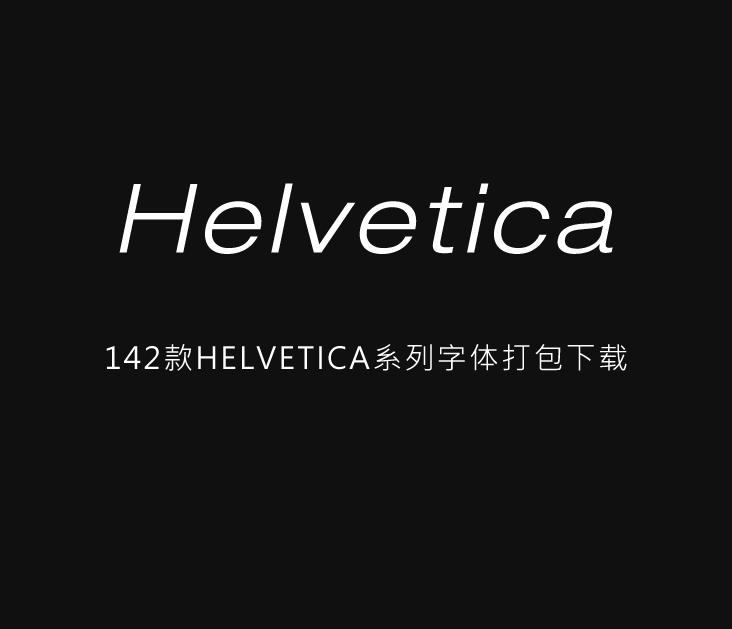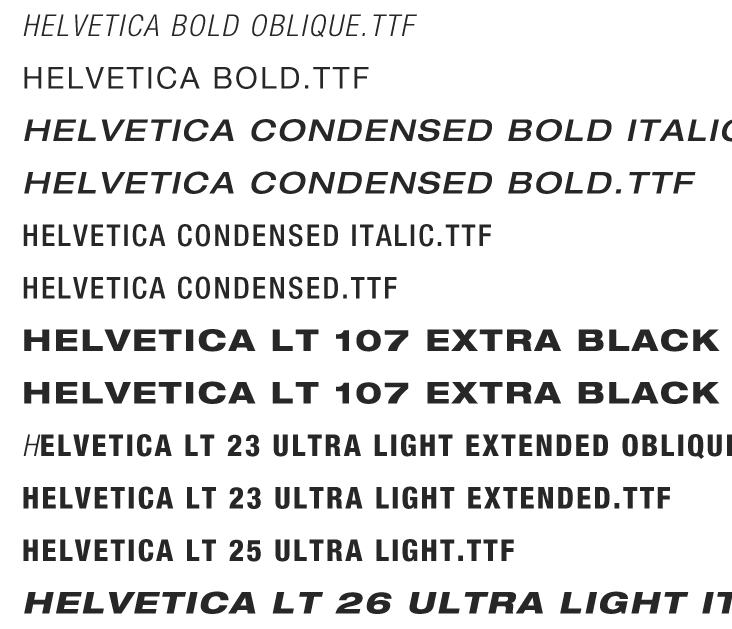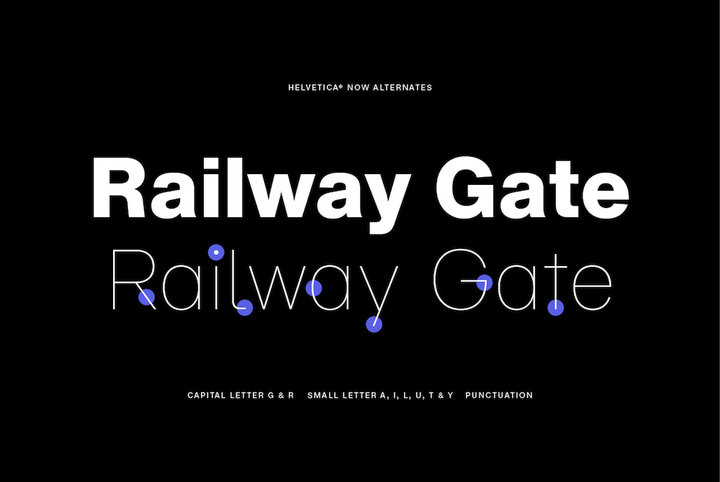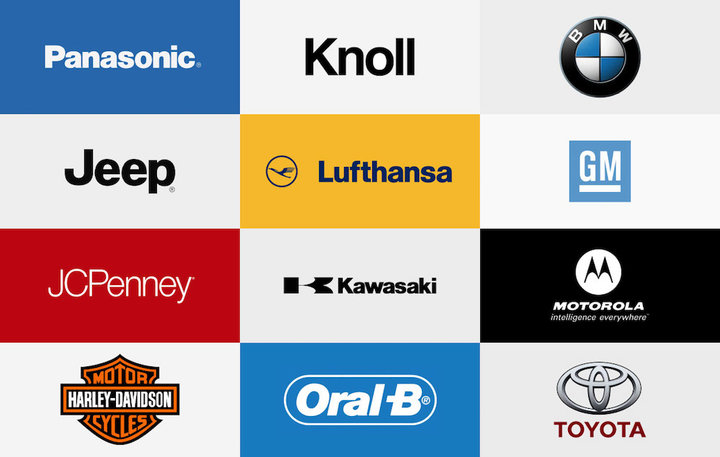
Helvetica是一种被广泛使用的的西文字体,于1957年由瑞士字体设计师爱德华德·霍夫曼(Eduard Hoffmann)和马克斯·米耶丁格(Max Miedinger)设计。
Helvetica是由米耶丁格和爱德华德·霍夫曼在瑞士哈斯铸造所作为排版铅字制作的。当时人们熟悉的是“国际字体风格”(也称为“瑞士风格”),比如Josef Muller-Brockmann在1896年推广的Akzidenz Grotesk这类无衬线字体,而哈斯希望能设计一套新的无衬线字体能够与Akzidenz Grotesk在瑞士市场上竞争。最初的名称是“Neue Haas Grotesk”,意为“哈斯的新无衬线铅字”,后来曾考虑改为Helvetia(源自拉丁文的“瑞士”一词),不过最终改为Helvetica,在拉丁文中意为“瑞士的”。
Helvetica被广泛用于全世界使用拉丁字母和西里尔字母的国家。同样的风格也被移植到希腊字母、希伯来字母和汉字。
Helvetica是苹果电脑的默认字体,与微软常用的Arial字体相似,但非自于它。2007年是helvetica诞生50年,作为在平面设计和商业上非常普及和成功的一款字体,英国导演Gary Hustwit专门为她拍摄了一部纪录片《Helvetica》。
Helvetica出自瑞士字体设计师Eduard Hoffmannh和Max Miedinger之手,体现了瑞士设计的理性主义精神,同时被认为是现代主义设计理念的典范。
《Helvetica》这部纪录片采访了老中青三代字体设计家,50、60年代进入设计界的老人深受现代主义影响,认为字体并不传达资讯,而要让人简单清晰的读懂文字;中年一代深受反主流文化的革命和后现代主义影响,认为设计应当是个人主义的,其极端就是难以辨认的垃圾风格的字体;青年一代设计师介于两者之间,他们更喜欢使用Helvetica,但不是没有选择的滥用。
在50年代,现代主义设计由于其风格简洁、朴素,并运用数量化的设计方法(典型的如画网格),Helvetica得以应用到商业设计中,成为大公司、政府等机构的御用字体,被70年代反主流文化的设计师们认为象征“权力”并且非常无聊。新一代的设计师,1970年代之后出生的人,虽然同样强调个性,但是他们同时不拒斥商业和机构,他们选择Helvetica放到合适的地方。
2019 年 4 月,Helvetica 字体更新了,距离这个传奇西文字体的上一次更新已经过去了 35 年。
之所以被称为传奇,是因为这个诞生于 1957 年的字体长盛不衰,从美国航空、松下电器、雀巢到纽约地铁标识系统,都有 Helvetica 的身影。它可能是应用最广泛的现代字体。
Helvetica 流行的原因是它就像一个透明的玻璃容器,能够清晰、可靠、中立地传达信息,同时让人意识不到字体的存在。有人把 Helvetica 称为「无衬线字体的终极形式」。
因此,它的更新周期也非常漫长。Helvetica 的上一次更新是在 1983 年推出的 Helvetica Neue(意为「新的 Helvetica」),新字体增加了更多的粗细和宽度,以适应桌面排版。
这一次,Helvetica 的改版历时 4 年,而且更加彻底,字体设计师重绘了每一个字体,并增加了 3 种视觉尺寸,目的很简单:适应更小的屏幕阅读。
从诞生到两次更新, Helvetica 字体的演进也代表了平面设计风格和传播介质的变迁。而最近的这次更新,Helvetica 似乎已经落后了。
这一次更新了什么?
Helvetica 这次更新后的名字叫 Helvetica Now。
拥有 Helvetica 字体版权的 Monotype 公司写了一篇短文介绍这个新字体,它的更新主要有三个方面。
1、三种视觉尺寸(Optical Size)
Helvetica Now 有三种适用不同场景的视觉尺寸:Micro、Text 和 Display。其中 Display 主要用于标题文本,Text 用于正文,Micro 是这次新推出的尺寸,用于在平板电脑、智能手表等小尺寸高分辨率屏幕上。
参与此次字体重制的设计师在接受 TheVerge 采访时解释了这样做的原因,对于他来说,Helvetica 通常在 6pt(点,字体度量单位,1pt = 1/72 inch = 0.3528 mm)时就变得难以辨认。
Micro 尺寸调整了字形和字距,可以让它即使在 3pt 下,也能够被轻松辨认。
2、可替换字形
为了给设计师更多的选择,Helvetica Now 为一些字母提供了可替换的字形,过去,设计师只能手动进行修改。比如,大写「R」最后一笔可以变直,小写的「a」可以用单层的结构,小写「i」的点可以用圆形。
3、字体细节调整
「Helvetica Now 不是一次更新,而更像是一次重制。」
这次字体的改版历时 4 年,Monotype 的设计师重绘了每一个字符,Helvetica Now 包含 9 个字重(从极细到超黑),3 种视觉尺寸和 2 种斜体,而每一个样式下包含字母、数字、符号等共有 815 个字符,所以,字体设计师义工重绘了四万多个字符。
微博用户 @字体主义 把 Helvetica Now 和旧版的 Helvetica Neue 做了一个对比,认为「字符整体更现代了,更偏几何风格。」
▲蓝色为 Helvetica Now,红色为 Helvetica Neue. 图片来自:@字体主义
Helvetica 为什么成为传奇
Helvetica 的诞生是二战后全球化思潮和设计上的现代主义交织的结果。
独立制片人导演 Gary Hustwit 的纪录片《Helvetica》详细解答了这个字体诞生的背景。战后,人们开始致力于减少国家间的贸易壁垒,促进自由交流和贸易,许多国际协定和组织都在这个时期产生,如世贸组织、世界银行等。
文化上的全球化思潮同样明显,战后百废待兴的背景也影响了设计思想的「除旧迎新」。两个因素交织,设计上的现代主义主要体现为实用主义观点。比如,当时有设计师认为建筑应该是「为居住而准备的机器」,汽车是「旅行的机器」。
▲ 一栋现代主义大楼
现代主义设计师普遍抗拒从古希腊和中世纪继承下来的旧风格、旧结构,他们拒绝在设计中采取装饰性的图形,转而强调使用纯粹的几何形式。
Helvetica 是这些设计思潮的集中代表。它起源于瑞士,是典型的简约、自然、人性化的风格。
关于 Helvetica 诞生已经有非常多的记录,20 世纪 50 年代,老牌的字体公司哈斯铸造厂(Haas Foundry)为旗下的头牌无衬线字体 Haas Grotesk 创造了一个更现代化的版本 Neue Haas Grotesk,它就是 Helvetica 的前身。
▲ 设计 Helvetica 的 Max Miedinger 和 Eduard Hoffmann(右)
为了在美国推销这款新字体,公司的字体总监对 Neue Haas Grotesk 进行了微调,并将其改名为 Helvetica(意为「瑞士的」),最终这款字体获得了全世界的认可。
Helvetica 的字形足够完美,甚至被设计师称为「无衬线字体的终极形式」,更重要的是它非常符合实用主义的思潮,没有复杂的装饰性元素,就像一个透明容器,只供放置、展示和组织信息,读者甚至意识不到字体的存在。
一位设计师回忆了 Helvetica 出现的意义:上世纪 60 年代的企业标识系统一般由各种奇怪的形状、蠢笨的照片和傻气的字体组合而成。
Helvetica 的出现改变了这种过时的做法,设计师不再使用虚伪的人物和混乱的字体来做平面设计,只需要一张白纸,大幅留白,用 Helvetica 写上公司名或宣传语,就能起到意想不到的效果。
▲「没有人物,没有虚伪的笑容,就是一瓶美丽的冰镇可乐。就是这么真实,句号。」来自:纪录片 Helvetica
你能想象那是多么令人振奋和激动吗?就如同你刚爬出一片沙漠,满嘴都是肮脏的沙尘,然后有人给你递上一杯清澈见底、令人精神一振的、冰镇的纯净水。让你所有的不快、历史包袱都抛之脑后。
一位设计师如此说到。
字体为传播媒介服务
Helvetica 诞生时,字体主要还是用于印刷品,而它的优雅、可靠、中立也帮它走过了桌面 PC 时代。
纪录片《Helvetica》提到,20 世界 7、80 年代,因为 Helvetica 被大范围应用甚至有滥用的嫌疑,很多叛逆的设计师开始有意对抗这种风潮,「一本印着简单的 logo、商务人士,使用 Helvetica 字体,并有大量留白的册子,基本等等同于无聊。」但进入 90 年代后,不少理性的设计师又重新回归了 Helvetica。
1982 年,Helvetica 开始第一次大的更新,新字体增加了更多的粗细和宽度,以更好地适应桌面排版。
苹果从 Macintosh 电脑时期开始就一直收录了 Helvetica 字体。早期,Macintosh 将衬线字体 Apple Garamond 作为系统字体。2002 年,无衬线字体 Myriad 取代 Apple Garamond 成为苹果的官方字体。
▲ 从 Apple Garamond 到 Myriad. 图片来自:魚生臣
在乔纳森·艾维(Jony Ive)成为苹果首席设计官后,苹果在设计风格上有了大的转变。扁平化的 iOS 7 开始将 Helvetica Neue 作为系统默认字体,从 OS X Yosemite 开始,Mac 上也开始把 Helvetica Neue 作为默认字体。
Windows 上的默认字体 Arial 也是 Helvetica 的衍生字体,因为它是微软和 Monotype 共同开发的,其比例、字距、行距和比重都依照了 Helvetica 的设计。尽管设计界认为 Arial 不如 Helvetica 优雅,但它在很多时候满足了同样的需求。
但在进入更加碎片化、屏幕更小的移动时代时,Helvetica 已经有点无法满足需求了。
2015 年,iOS 9 将默认字体改成了苹果推出的旧金山字体(San Francisco),以替代之前的 Helvetica Neue。
这不是一个头脑发热的举动,因为苹果在同期推出了 Apple Watch,而 Helvetica Neue 在小字号上一向表现不佳。
设计师 Akinori Machino 总结了设计圈对 Helvetica Neue 的吐槽:「如果你输入小字号的 Helvetica 文字,你会发现易读性很低,显得模糊。有些文字交叠在一起,难以辨识。」
▲「Helvetica Sucks」. 图片来自:Erik Spiekermann